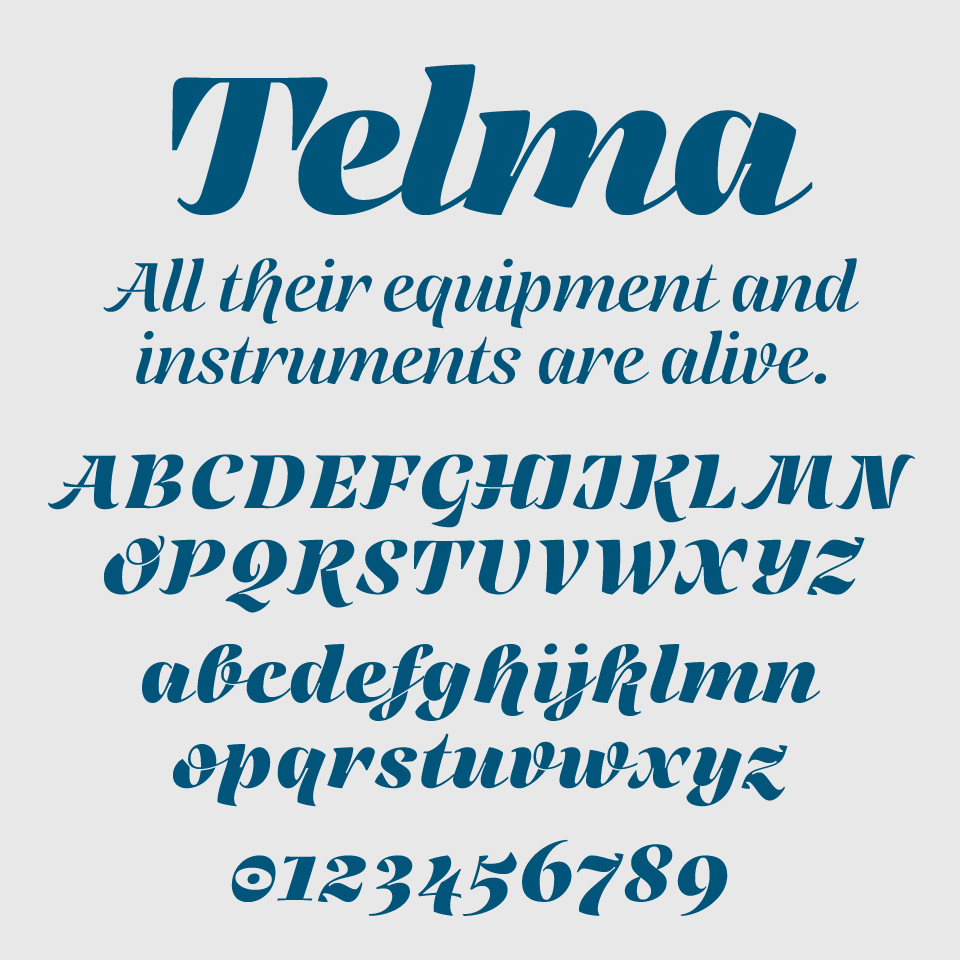
Telmaフォントは、筆記体の流麗さとレトロな広告文字のような遊び心を兼ね備えた、印象的なスクリプトフォントです。
一文字ごとに微妙な起伏があり、太さのグラデーションが視線を誘導するように流れていきます。筆で描かれたような抑揚がありながらも読みやすさを保っており、華やかさと実用性が共存しています。
バレエのポスターや高級洋菓子のパッケージなど、優雅でドラマチックな演出をしたい場面にぴったりです。女性的な柔らかさの中に、少し懐かしさを感じるニュアンスがあるフォントです。